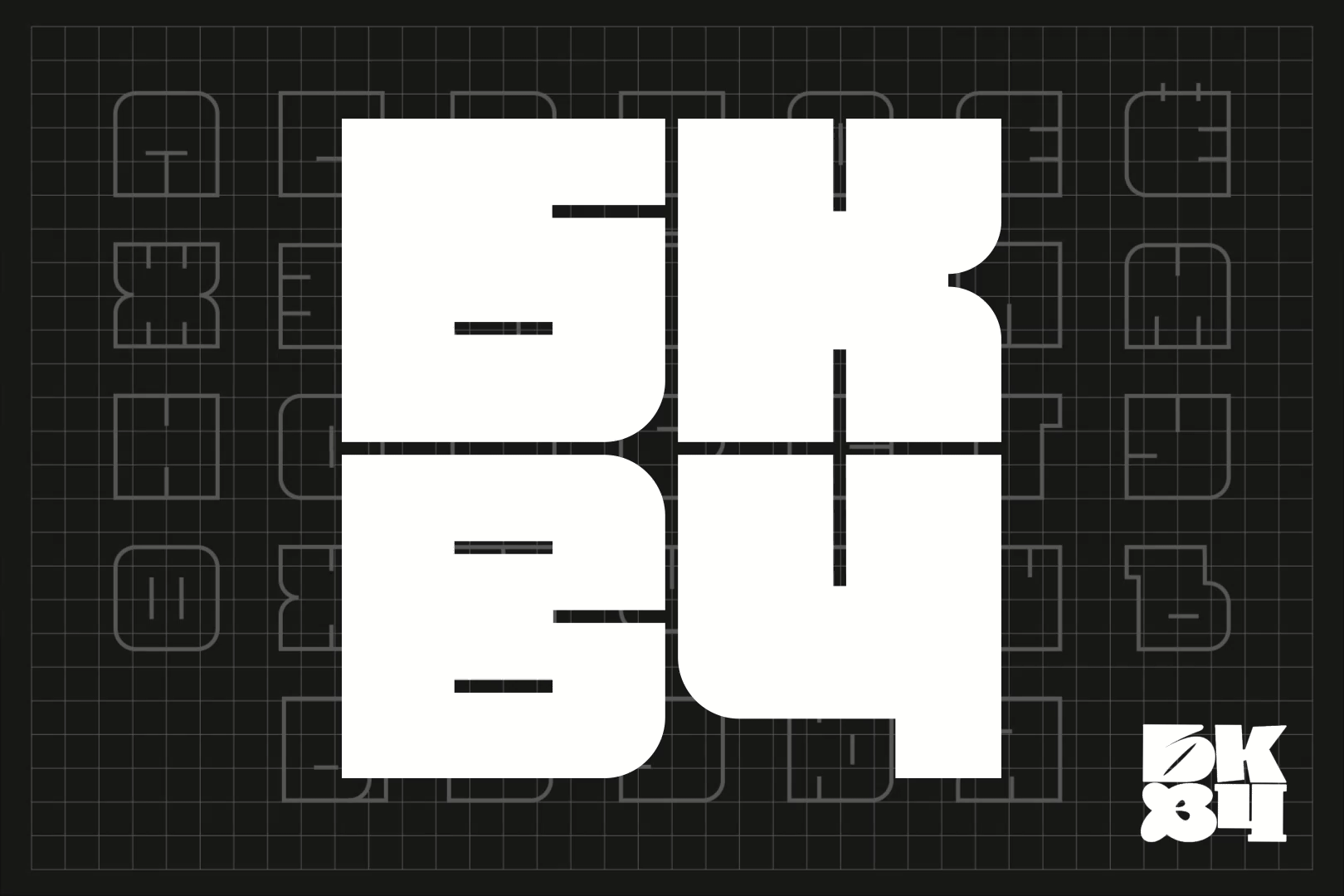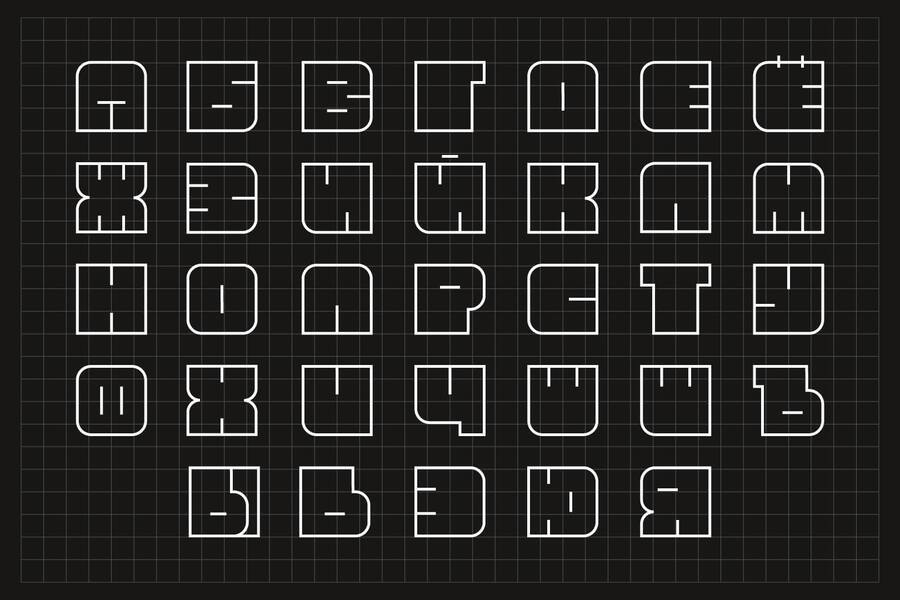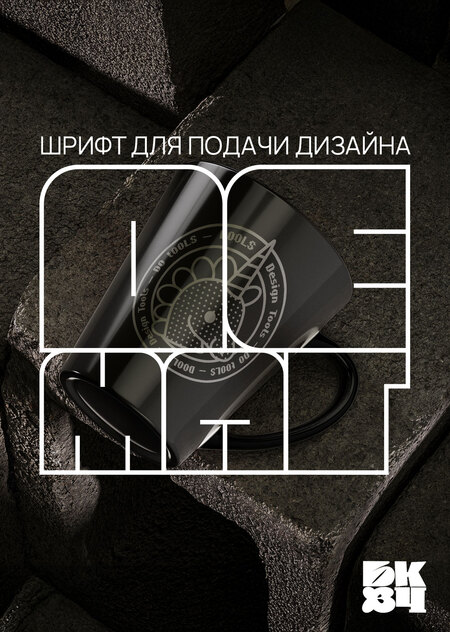
АКЦИДЕНТНЫЙ ШРИФТ ДЛЯ ПОДАЧИ ДИЗАЙНА «ДЕМАГ»
Некоторое время назад я поняла, что хочу делиться находками в области графического дизайна, интересными и красивыми кейсами, новостями и подборками тех дизайнов, что запали мне в душу. Это решение вылилось в формат ежемесячного цифрового журнала «DeMAG» или Design Magazine. Выпуски, которые появились за это время можно почитать на моём сайте в разделе demag/media
Идея, которую я использую для оформления своего журнала — это крупные линейные буквы-фреймы, которые несут текстовую информацию, но не перекрывают визуальную составляющую. В оформлении журнала я использую только само название DEMAG на латинице.
А потом мне повстречался «Буквальный челлендж», я решила в нём поучаствовать и реализовать целый алфавит для подачи дизайна на кириллице, как продолжение идеи оформления моего журнала.
Представляю свой концепт акцидентного шрифта для презентации дизайнов «ДеМАГ». Суть шрифта в том, что его буквы и слова из них могут не только передавать месседж, но и служить шейпами (формами) и фреймами (рамками) для подачи дизайнов и оформления кейсов. Добавила в проект так же словарь дизайнера. Чтоб мы с вами не забывали, как много всего знаем, и какую важную работу делаем, друзья дизайнеры.